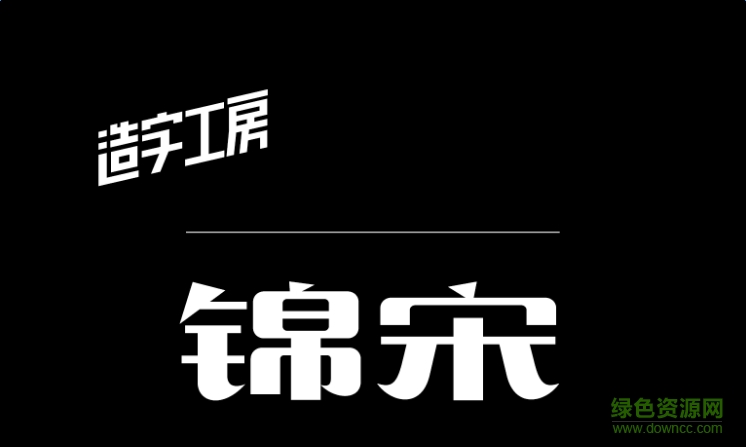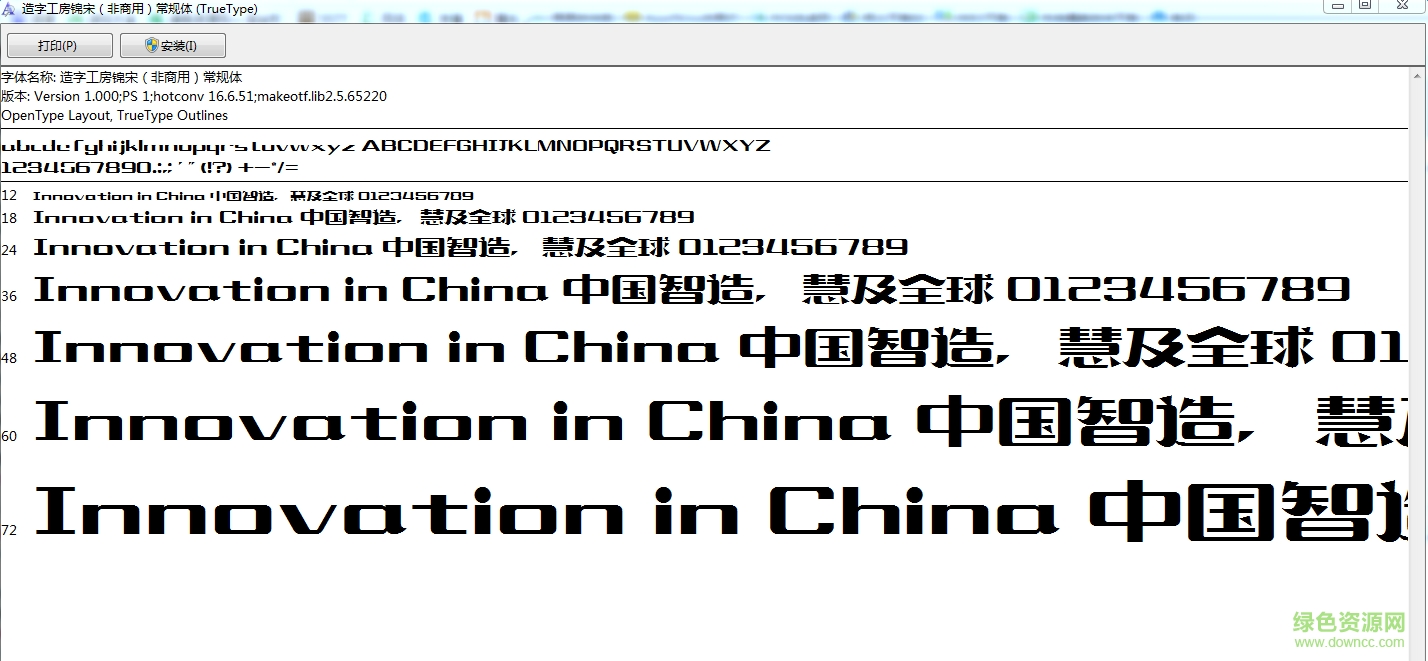
造字工房錦宋體字體
造字工房錦宋體是一款造字工房類簡約清爽風(fēng)格字體軟件,錦宋體整體效果融合工整,沒有一絲多余的筆畫,非常的醒目,在標(biāo)題設(shè)計方面有著不錯的應(yīng)用,還有更多好看字體盡情期待,歡迎到綠色資源網(wǎng)下載體驗!
字體介紹
造字工房錦宋體筆畫簡潔、筆鋒柔和典雅,曲線舒展,勾畫處理部分如新月牙,點、提尖角跟撇的圓潤處理相互呼應(yīng),剛?cè)岵?、工整而不失精巧,最大程度的展現(xiàn)筆畫的柔和秀美,濃筆重彩,有極強的視覺表現(xiàn)力。
造字工房錦宋體